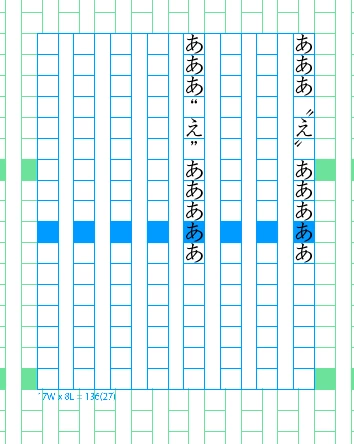
縦組みでPro6フォントでの“”(ダブルミュート)の扱いについて
環境設定にて「縦組み用引用符を横組み用として使用する」をoffにして使っています(1行目リュウミンPro)
Pro6フォントを使うと縦組み用に変換されません(2行目)
先の設定はPro6フォントには対応しない様です
Pro6フォントを使うに当たり都度意識して修正する必要が出てきます
Proフォントのように使い勝手の良い方法あるでしょうか
また先の「縦組み用引用符を横組み用として使用する」のon,offにすることで影響するケースあるでしょうか
引用符に等幅全角字形を適用してください。これで縦組用のグリフに置換されます。
モリサワのProとPr5以降では、引用符のグリフが異なります。これはAdobe-Japan1の改訂と、モリサワの互換性重視の方針が交錯した、ちょっと複雑な事情が背景にあります。
モリサワPr5以降で引用符を縦組用にグリフ置換するには、等幅全角字形を適用するのが筋の通った対処方法です。
> また先の「縦組み用引用符を横組み用として使用する」のon,offにすることで影響するケースあるでしょうか
ありますよ。以下を参考にしてください。
InDesignで引用符を合成フォントの特例文字で欧文フォントにしている場合の引用符のアキ量設定の文字クラス
proを使っていた時は「縦組み用引用符を横組み用として使用する(off)」で文中で特に意識することなく自動で変わっていましたが、pro6を使う際には意識的に適用する必要があるということで、使用書体による違いを把握していねければならず厄介なことになっている気がします。
自動を使わず初期値設定をonにし、pro、pro6共に同じ挙動にしたほうが間違いの減少なりそうに思えました(確かにこの設定は互換に関する括りとなっているようなので初期値はonかな)
同じ挙動を示す引用符を正規表現で表すための範囲セットってあるのでしょうか
全てを羅列する他ないのでしょうか
引用符をどうやって処理するのか考察したことがあるので、参考にしてください。私は現状の機能がベストの落としどころだと思います。
InDesignで引用符をどうすればいいのか
>同じ挙動を示す引用符を正規表現で表すための範囲セットってあるのでしょうか
>全てを羅列する他ないのでしょうか
一重引用符と二重引用符の2種類([‘’“”])だけを処理対象にすれば問題ないです。